MdN EXTRA Vol. 5 絶対フォント感を身につける。
「絶対フォント感」とは、広告やポップ、出版物、掲示物に使用されているフォント(書体)が何のフォントか見分ける能力を意味する。
そんな絶対フォント感についてMdNでは2015年を皮切りに毎年のように特集が組まれてきた。「MdN EXTRA Vol. 5 絶対フォント感を身につける。」では、過去の「絶対フォント感」の特集3号分を「総合編」「明朝体編」としてムックとしてまとめ、新たに「ゴシック体編」を新規記事として追加した「絶対フォント感を身につける。」完全版となっている。
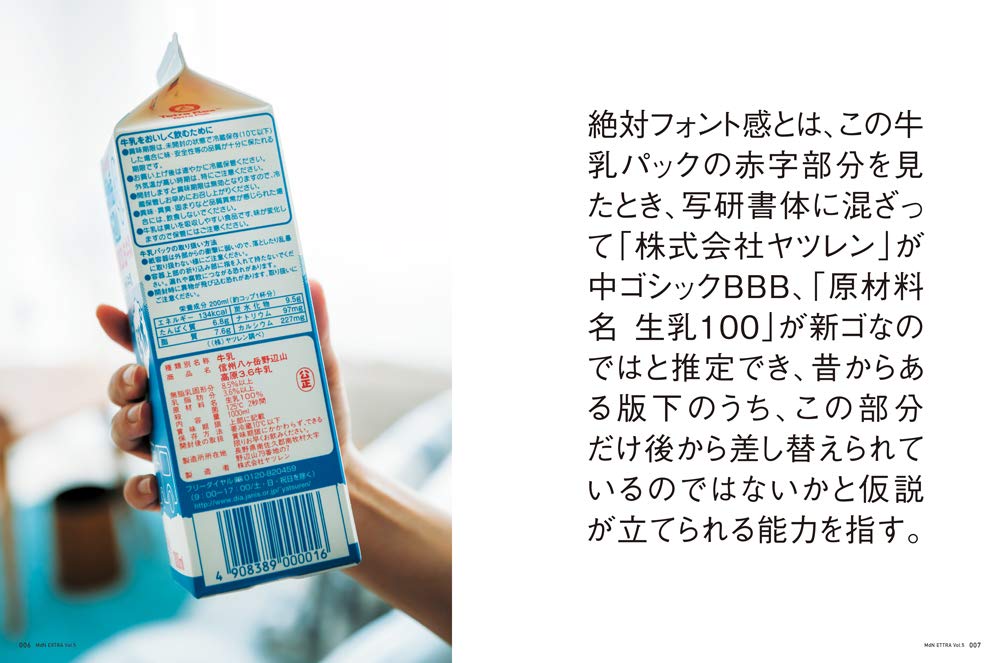
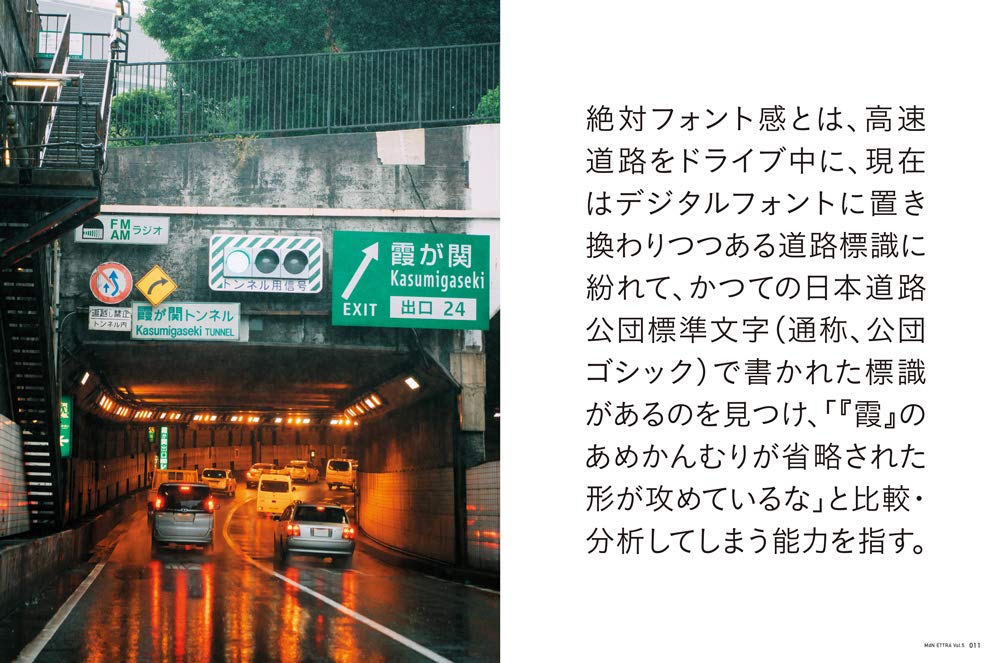
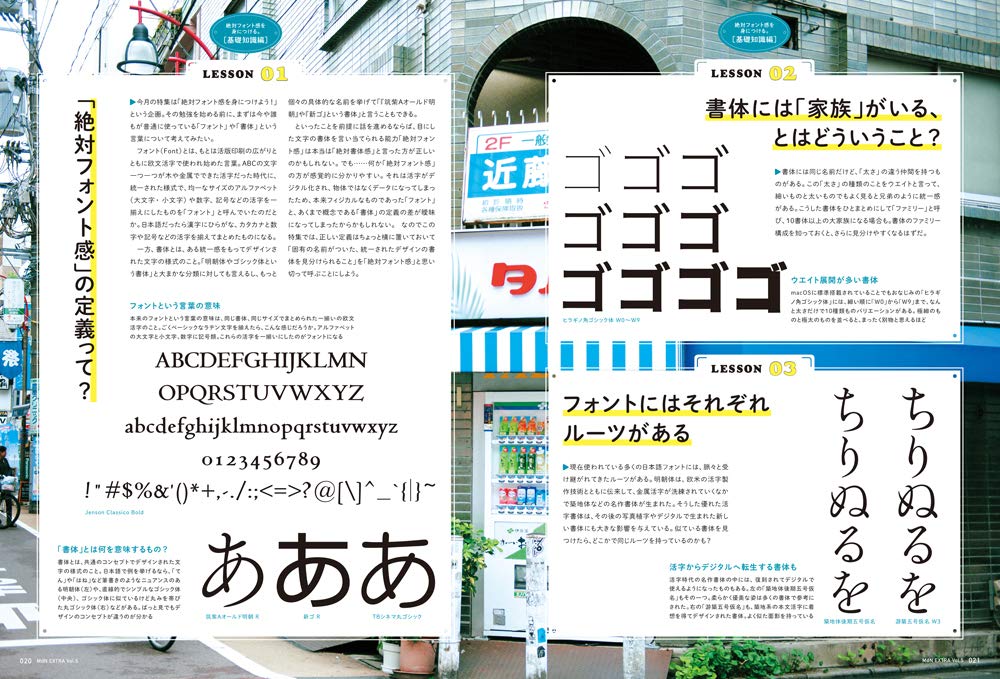
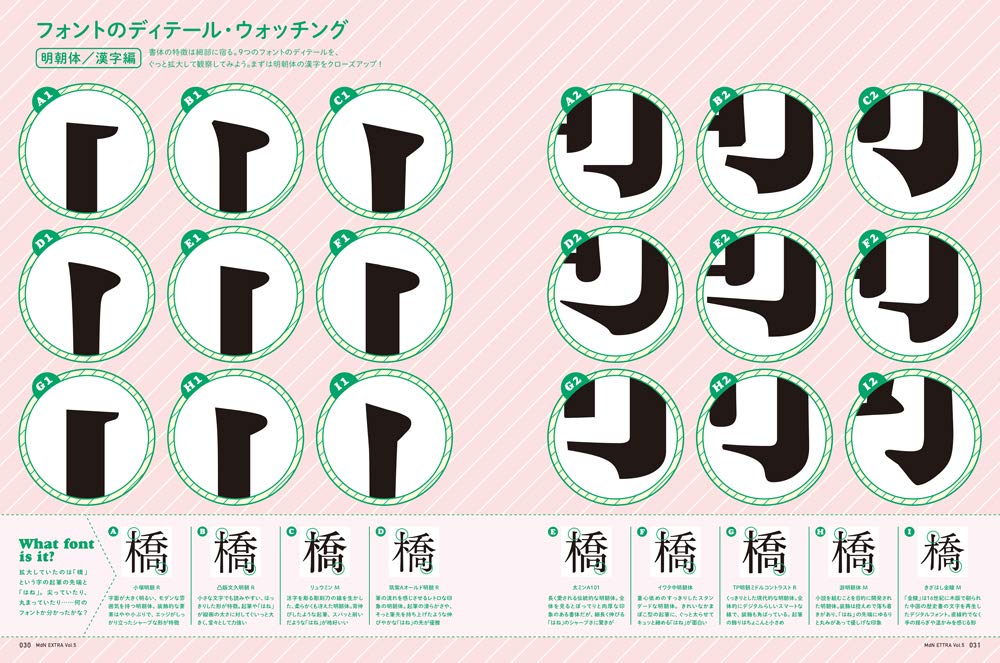
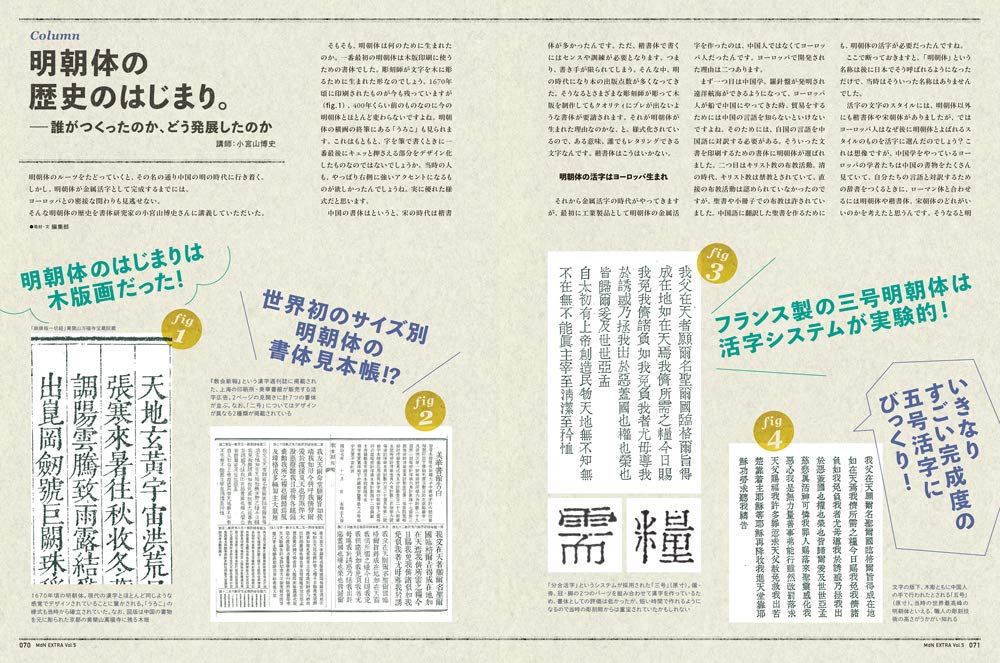
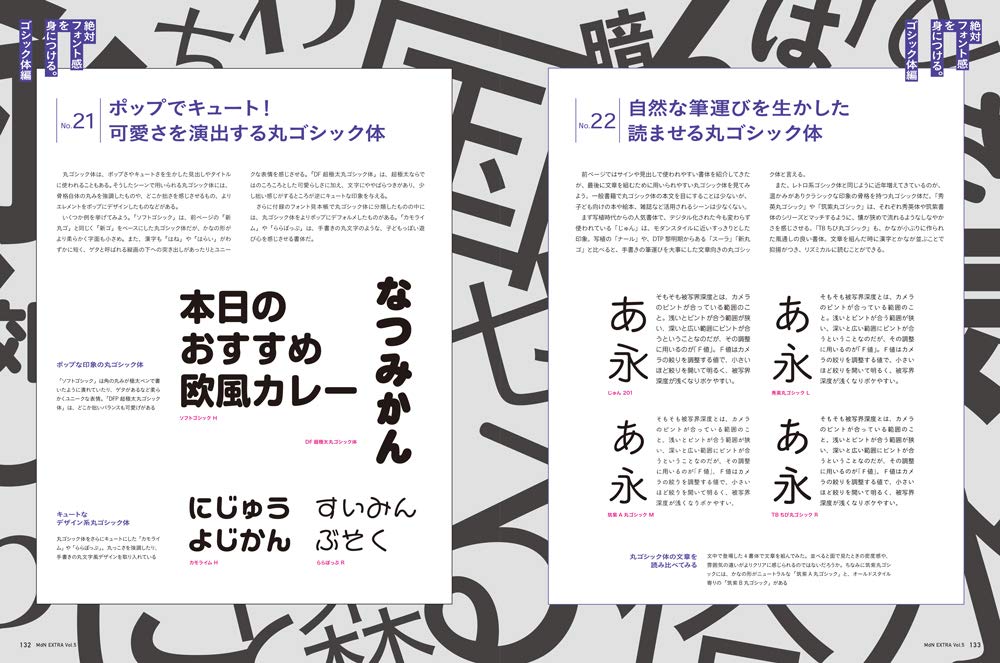
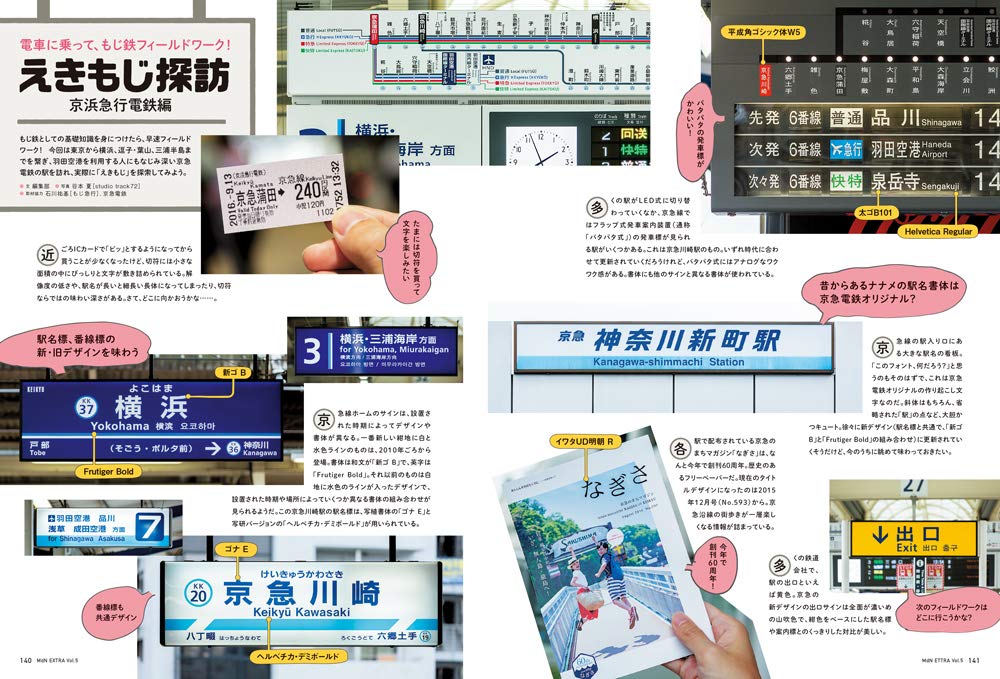
「絶対フォント感を身につけるためのフォント見本帳」が付録で付く!
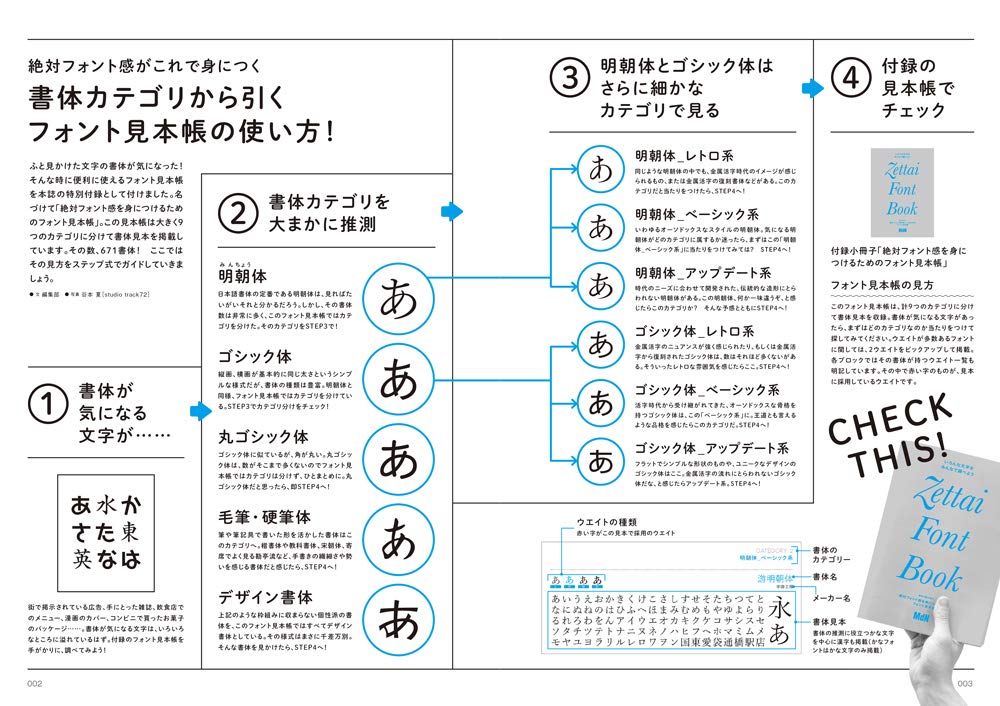
また合計176ページ、全650書体超を収録した書体見本帳「絶対フォント感を身につけるためのフォント見本帳」も付録についた。「絶対フォント感を身につけるためのフォント見本帳」は、「明朝体」「ゴシック体」「丸ゴシック体」「毛筆・硬筆体」「デザイン書体」といったカテゴリに分けられたフォント見本帳になっている。
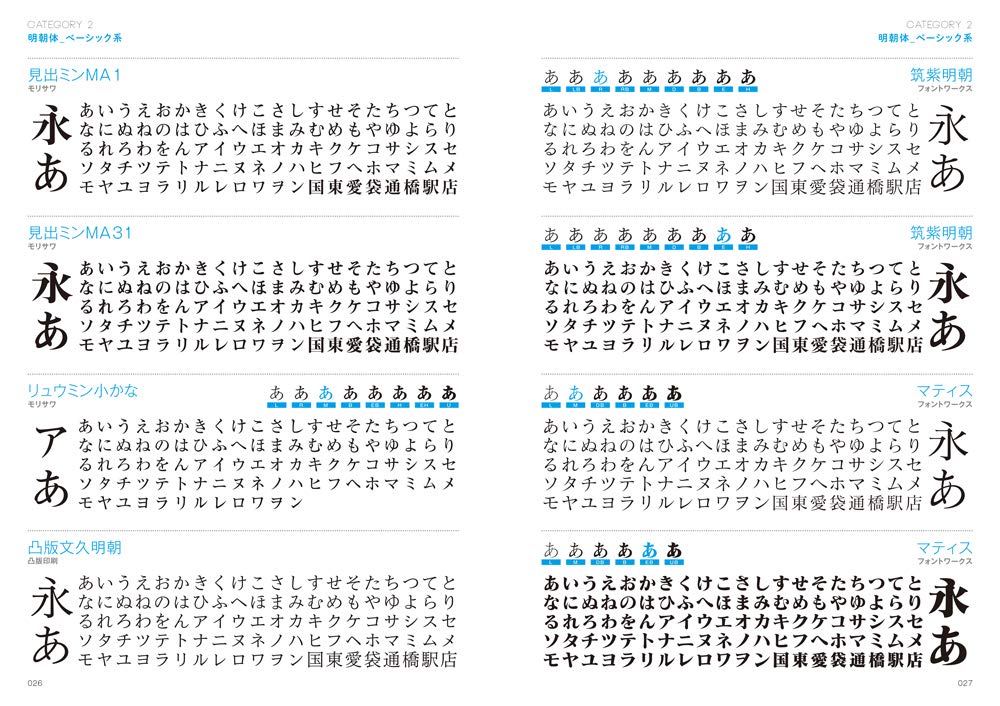
「絶対フォント感」を総合的に追究した完全保存版ムック!
さまざな書体を見分け、言い当てることの出来る能力「絶対フォント感」。
デザイン誌MdNでは、そんな「絶対フォント感」を身につけるべく、
2015年に特集を行ったところ、大きく話題を呼び完売号となりました。
その後、計3回の「絶対フォント感」特集はいずれも大好評。
このムックは、それら過去の「絶対フォント感」特集3号分を
「総合編」「明朝体編」としてまとめ、加えて今回新たに「ゴシック体編」を新規記事として追加。
書体について、さまざまな理解が進むムックになりました。
さらに、計176ページ、全650書体超を収録した書体見本帳「絶対フォント感を身につけるためのフォント見本帳」も付録に!
「明朝体」「ゴシック体」「丸ゴシック体」「毛筆・硬筆体」「デザイン書体」と
カテゴリがわかりやすく分けられた見やすいフォント見本帳です。
街中で看板を見たり、家で本を読んだりしていて気になった書体が出てきたら、これで調べてみて下さい。
【主な内容】
ARTICLE 1 総合編
・「絶対フォント感」の定義って?
・フォントにはそれぞれルーツがある
・書体の特徴はディテールに表れる
・文字の「明るさ」はふところの広さ? etc.
ARTICLE 2 明朝体編
・明朝体の「漢字」は工業製品のような機能美が!
・明朝体の「ひらがな」は感じに比べて体臭がある!
・明朝体を大まかにカテゴリ分け
・明朝体の漢字の造形、チェックポイント
・現在の明朝体の源流となる活字がある! etc.
ARTICLE 3 ゴシック体編
・ゴシック体は幾何学的……とは限らない?
・ファミリーの遺伝子は骨格に宿る
・ゴシック体をカテゴリで分けてみよう
・活字を受け継ぐレトロ系ゴシック体 etc.
そのほかのコーナー
・写植モダン。――現代に息づく写植の文字を味わう
・明朝体の歴史の始まり。――誰がつくったのか、どう発展したのか
・ひらがなの形で辿る明朝体の系譜まるわかり!
・もじ急行PRESENTS もじ鉄のススメ!
【特別付録小冊子】
絶対フォント感を身につけるためのフォント見本帳
▼絶対フォント感を身につける。「明朝体編」特集内容
〈明朝体の基礎を知る〉の巻
・明朝体の「漢字」は工業製品のような機能美が!
・明朝体の「ひらがな」は漢字に比べて体臭がある! …ほか
〈レトロな明朝体を知る〉の巻
・復刻、改刻、インスパイア。レトロ系明朝体は奥深い
・明朝体の歴史的書体が今のフォントに影響を与えている! …ほか
〈ベーシックな明朝体を知る〉の巻
・ベーシックな明朝体はどこをとってもバランスがいい!
・実際に組まれたベーシックな明朝体で書体を当てていく …ほか
〈アップデートされた明朝体を知る〉の巻
・明朝体、時代の要請でいまだ進化の途中
・太さのバリエーションがグラデーションのようにある明朝体 …ほか
〈明朝体を比べて考察する〉の巻
・ひらがなだけを見て書体を言い当てられるのか
・漢字だけを見て書体を言い当てられるのか …ほか
【クイズ】
日本のフォントを解明!
世界を旅する! フォント観光大使
【Column】
明朝体の歴史のはじまり。――誰がつくったのか、どう発展したのか
講師:小宮山博史
◆付録小冊子◆
176ページ、668書体を掲載した「絶対フォント感を身につけるためのフォント見本帳 2017」。付録としては2015年版や2016年版にも付いてきたが今回も2017年版として同梱されている。
【特集1】
明朝体を味わう。
明朝体ソムリエになりたい
ワインのラベルを見て、品種や産地を手がかりにその一本のことをいろいろと想像し、
最後に自分の舌で楽しむ。
そんなワインのテイスティングのように明朝体を味わえたら、読書をしたり
グラフィックを見る喜びがより大きくなるはず。
タイプフェイスデザイナー、書体研究家、グラフィックデザイナー、文筆家、
フォントベンダーの関係者など計15人の識者の言葉を手がかりに
「名品」と言える27種類の明朝体の成り立ち、
そして味わいを解説します。
【紹介する明朝体】※誌面登場順
◆築地体前期五号
歴史が発酵させた味。日本の明朝体はここから始まる
◆築地体初号
当時の面影を色濃く残す古代ワインのような明朝体
◆築地体後期五号
現代明朝体の始祖となるもぎたての果実のような成果
◆秀英明朝
改良を重ねて今がいちばん美味しい伝統の味わい
◆秀英初号明朝
江戸のクラシカルな香りが漂う粋な見出し明朝体
◆精興社書体
門外不出の格調高い一品。美しい謎に包まれた味
◆石井中明朝体(MM-OKL)
天才が手間ひまかけて美味をやさしく抽出した文字
◆イワタ明朝体オールド
文学を目でなめらかに十全に味わえる孤高の明朝体
◆モトヤ明朝
公的な場面で味わいたい、晴れがましさを感じる一品
◆凸版文久明朝
優しい軽みのある味わいでスッキリ爽やかテイスト
◆本明朝
刺激的で硬いテイスト。でもこの刺激、覚えがある?
◆A1明朝
情感あふれる味わい。言葉を選ぶほどの文字の個性
◆本蘭明朝
先進的な思想の明朝体。味わったことのないシャープさ
◆リュウミン
端正で落ち着いた表情。ひんやりとクールなテイスト
◆光朝
過去と未来が書体の中で交錯するハイブリッドな味覚
◆ヒラギノ明朝体
伝統をアップデートした雑味のない研ぎ澄まされた味
◆小塚明朝
機械的なまでに粒が揃った味わい。サイボーグ明朝体
◆丸明オールド
クラシカルでモダン。2つの異なる香りが広がる
◆游明朝体
この上質な味わいが新しい時代のスタンダードに
◆筑紫明朝
精製したばかりの米のように瑞々しく清潔な明朝体
◆筑紫Aオールド明朝
伝統の味わいを再定義、再構築したら新テイストに
◆第2期 筑紫明朝(筑紫アンティーク明朝/筑紫Q明朝/筑紫Aヴィンテージ明朝/筑紫Bヴィンテージ明朝)
伝統? 新創作? 明朝体の問題作といえる新テイスト
◆TP明朝
明朝体本来の情緒感を排したメカニカルなテイスト
◆貂明朝
かわいらしいけど媚びない飄々としたテイストの明朝
【登場する識者】※誌面登場順
祖父江 慎/小宮山博史/正木香子/橋本和夫/伊藤正樹/小野克之/藤田重信/鈴木 功/新井尚子/池田 暢/小塚昌彦/鳥海 修/草野 剛/西塚涼子/片岡 朗
■特別付録小冊子 明朝体テイスティングリスト
特集に連動した書体見本帳です。
特集で紹介する27種類の明朝体の書体見本と組み見本を掲載しています。
また書体の味わいを紹介する文章も用意しました。
LESSON 01 そもそも「フォント」ってなに?
LESSON 02 ひとつの書体だけど8つの書体?/03 フォントは誰かが時間をかけて作っている
LESSON 04 明朝体って単なる筆文字? 違います!
LESSON 05 明朝体にもいろんな「味」がある/06 アップデートされた新時代の明朝体
LESSON 07 ゴシック体は文字の骨組みがまるはだか!